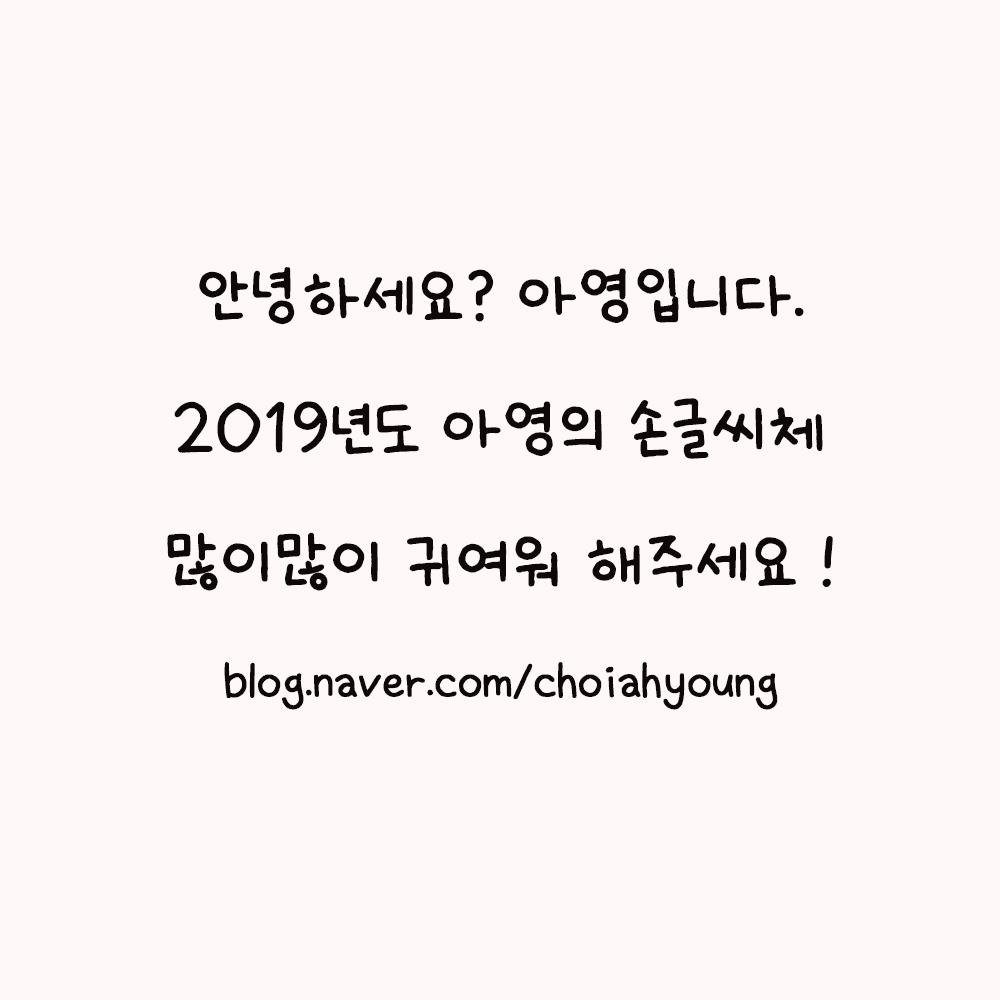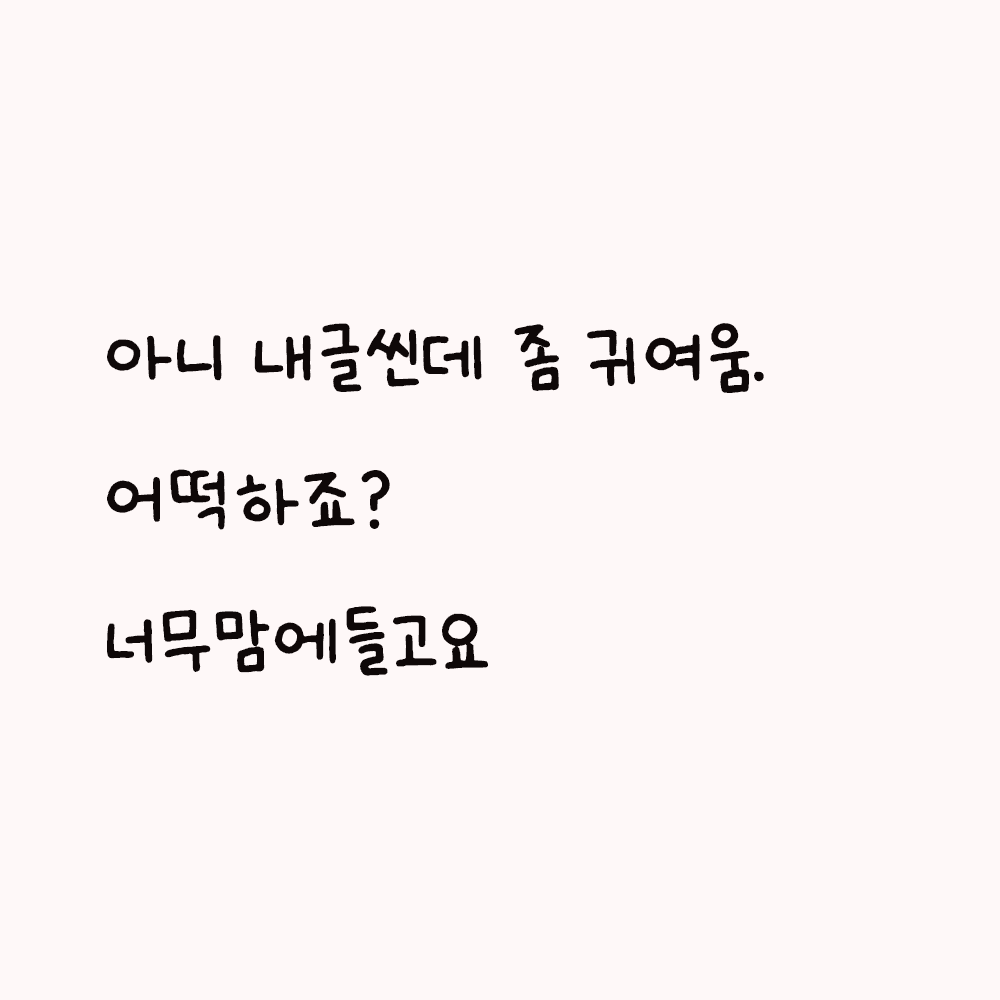
그리운 2019년도 아영의 손글씨
Griun Ahyoung's Handwrite In 2019
그리운 2019년도 아영의 손글씨 소개
안녕하세요 아영입니다. 글씨쓰고 다이어리꾸미기를 좋아하던 제가, 그동안 꼭 만들어보고 싶었던 직접 꾹꾹 써내려간 손글씨로 폰트를 제작했어요 ! 반듯하지만 동글동글해서 많이 귀여움 받았으면 좋겠습니다 ! 모든곳에서 사용 가능하나, 상업적 이용시 아래 네이버블로그에 댓글 꼭 남겨주시면 감사합니다 ! 똑같은 일상에 낭만 한 스푼 일상낭만, 아영